商用利用可の可愛いフリーフォントは、ライセンスを事前確認すれば無料で安全に使えます。特許庁の知的財産権ガイドラインに基づき、本記事では手書き風・丸文字・ガーリー系など15選を比較し、ダウンロードから利用規約確認まで解説します。
商用利用可の可愛いフリーフォントを安全に使うには、ダウンロード前に配布元のライセンスページで「商用利用可」「改変条件」「クレジット要否」の3点を確認することが確実な方法です。漢字対応・手書き風・丸文字など用途別に選べば、デザイン品質が一段と向上します。フォント選びに迷う方でも、本記事の診断フローを使えば5分以内に自分に合った1本が見つかります。
可愛いフリーフォントは3ジャンルで選ぶ
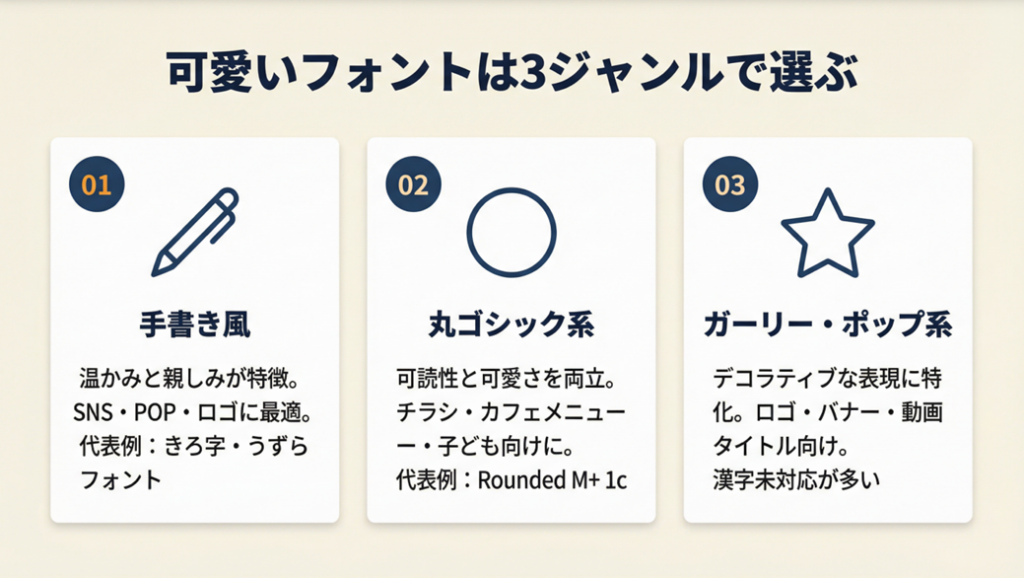
手書き風フォントは温かみと親しみが特徴
手書き風フォントは人の筆跡を忠実に再現したデザインで、SNSアイコン・POP・ロゴなど「親しみやすさ」を訴求したい場面に適しています。代表例として「きろ字」「うずらフォント」「殴り書きクレヨン」が挙げられます。漢字対応状況は配布元により異なるため、JIS第一水準(2,965文字)が含まれるかをダウンロードページで確認してください。漢字が中途半端にしか含まれないフォントを採用すると、印刷物や動画テロップで文字化けが発生し、制作後に差し替えが必要になります。
「きろ字」はJIS第一水準・第二水準漢字およびIBM拡張漢字まで収録した手書き総合書体フォントで、商用利用(フォントの再利用目的でない用途に限る)に対応しています。「うずらフォント」もJIS第一水準・第二水準漢字およびIBM拡張漢字に対応しており、約6,700文字を収録した商用利用可能なフォントです。どちらも一般的な日本語文章では文字化けが起きにくい充実した漢字セットを備えています。
手書き風フォントの主な配布元としてFont Free 手書き一覧があり、商用利用可フィルターで絞り込めます。同人誌・手作りショップのラベルには「きろ字」が視認性と柔らかさのバランスに優れています。
フォント選びに成功したWebデザイナーは「『きろ字』『うずらフォント』などを使い、手書き系のロゴ制作がスムーズだった」と振り返っています(デザイン案件で使ったおすすめ可愛いフォント紹介)。
Q: 手書き風フォントで漢字対応のものはありますか?
A: 「きろ字」はJIS第一水準・第二水準漢字とIBM拡張漢字まで収録しており、「うずらフォント」も同様にJIS第一水準・第二水準漢字とIBM拡張漢字に対応しています(合計約6,700文字)。配布元ページの「収録文字数」欄で確認してから使用してください。
丸文字・丸ゴシック系は可読性と可愛らしさを両立
丸文字・丸ゴシック系は文字の角が丸く処理されたフォントで、チラシ・カフェメニュー・子ども向けコンテンツなど「柔らかい印象」を作りたい場面に向いています。「ぷっちふぉんと」「コーポレート・ロゴ(ラウンド)」「Rounded M+ 1c」などが代表的です。ひらがなに特化した可愛いフォントも充実しており、用途に合わせて選べます。
もじワク研究では丸ゴシック系を用途別に整理しており、ジャンル確認に役立ちます。丸ゴシックは明朝体と比べて本文への使用でも疲れにくい設計のため、LPや長文コンテンツの見出しにも活用できます。ポップな見出しと読みやすい本文を1フォントで統一できる点が、デザイン工数の削減につながります。
ガーリー・ポップ系はデコラティブな表現に特化
ガーリー・ポップ系フォントは星・ハート・装飾文字などを含む視覚的にインパクトのあるデザインで、ロゴ・バナー・動画タイトルなど「一目で目を引きたい」場面に有効です。ただし収録文字数が少なく漢字未対応のものも多いため、英語・カタカナ・ひらがなに限定して使い、本文には別フォントを組み合わせる運用が現実的です。英字フォントを組み合わせたい場合は無料英語フォントの選び方も参考にしてください。
Canvaマガジン:無料で使える可愛いフォント紹介では、日本語・英語フォントの組み合わせ例を確認できます。1デザインにポップ系は1〜2書体に絞るのが基本ルールです。
Q: 1つのデザインで複数ジャンルのフォントを混在させてもよいですか?
A: 混在自体は問題ありませんが、1つのデザインで使うフォントは原則2〜3書体までに抑えることで統一感が保てます。見出し用にポップ系、本文用に丸ゴシックという組み合わせが実務では多いです。
Q: Canvaに内蔵されているフォントは商用利用できますか?
A: Canva Pro に含まれるフォントはCanvaのライセンス規約内で商用利用可能です。ただし、Canvaからフォントファイルを書き出して他のソフトで使用することはCanvaの利用規約で明確に禁止されています。Illustratorでも同じフォントを使いたい場合は、別途フォントの配布元を探してダウンロードしてください。
ステップ1: フォントを選ぶ 3ジャンル(手書き風・丸ゴシック・ガーリー系)から用途に合ったジャンルを診断フローで選び、Font Freeまたはもじワク研究でフォントを1本決める。グラフィックデザイナーとしてフォント選びをキャリアに活かす方法も参考になります。
ステップ3: 仕組みを整える ライセンス確認シートとフォント証明書フォルダを作成し、以降の案件で確認工数がかからない体制を作る。